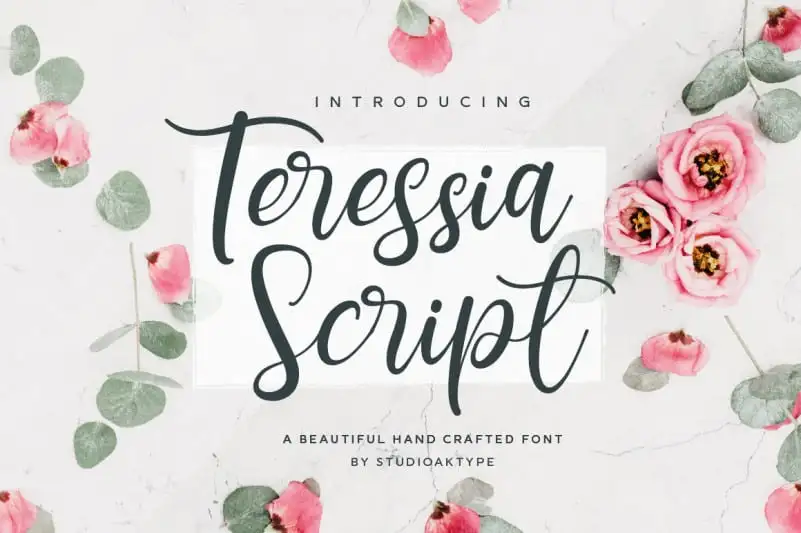
Teressia Script Font – Download Grátis
A Teressia Script Font é uma opção perfeita para designers que desejam trazer elegância à sua próxima criação. Esta fonte escrita a mão possui tonalidades naturais, oferecendo um toque único de fluidez a qualquer projeto. Perfeitamente adaptada aos diversos métodos de impressão, como emboss com ouro, costura e decoupage, ela tornará suas ideias de design ainda mais brilhantes e envolventes. Com uma aparência sofisticada e autêntica, você pode usar a Teressia para criar marcas de marca icônicas ou personalizar anúncios de forma única. Uma escolha certeira se você está buscando uma fonte que ressoa com elegância natural.
Designer: studioaktype